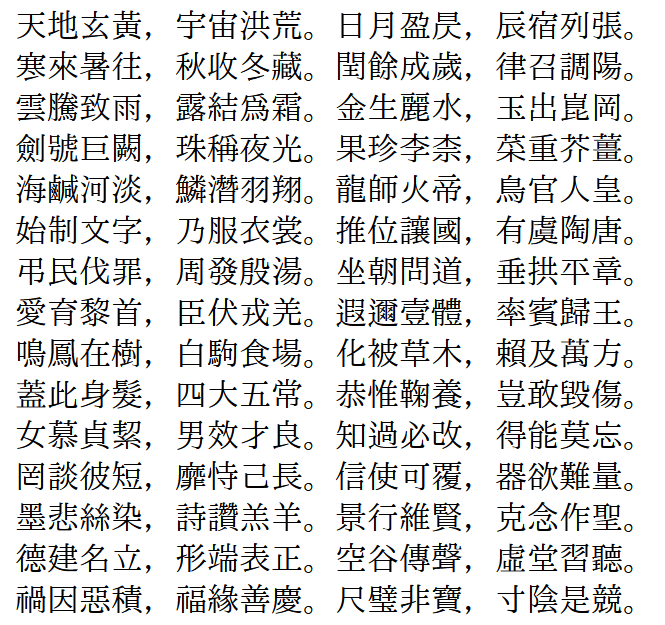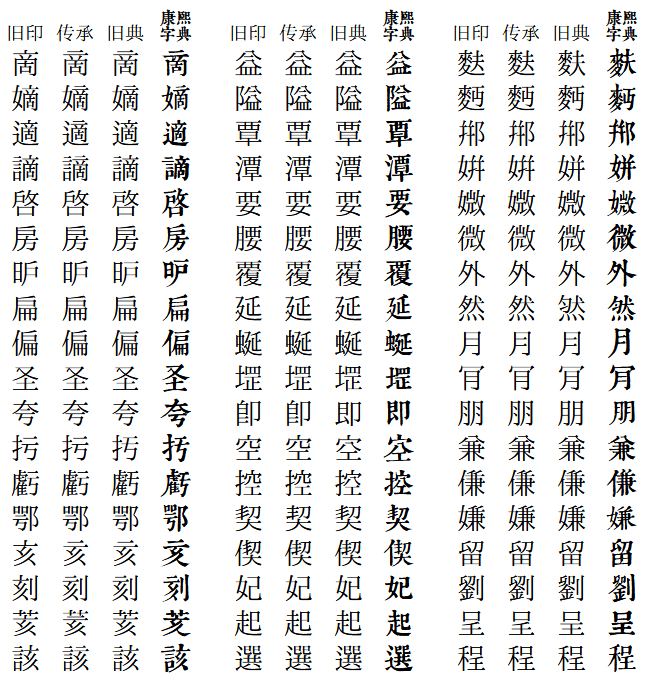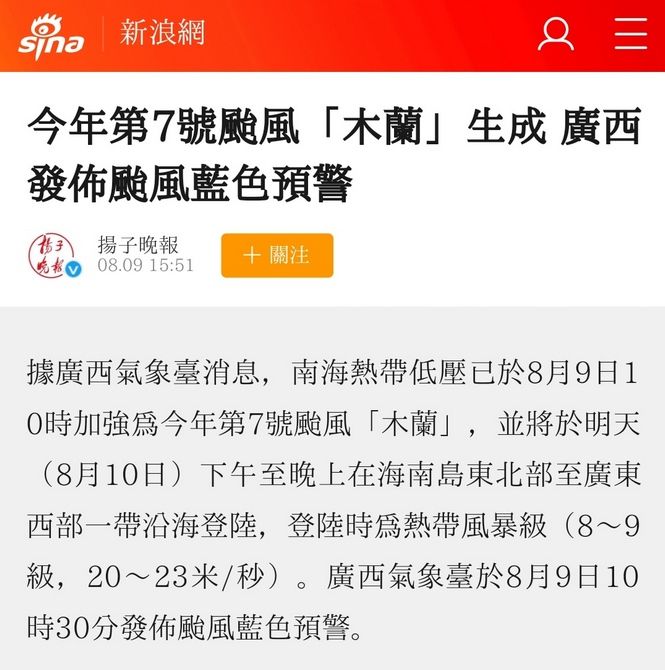
Huaying Mincho 华英明朝 華英明朝
Huaying Mincho 华英明朝是一套拥有传承字形、旧字形风格的中文字体。华英明朝共提供 3 种字形风格,并带有符合 IVD_Charts_Moji_Joho 标准的异体选择器。
1. 华英明朝 旧印体
旧印刷体,字形接近旧版 Windows 新细明体。
2. 华英明朝 传承体
传承字形版,综合参考了包括《康熙字典》在内的经典旧字形资料。
3. 华英明朝 旧典体
接近《康熙字典》中的字形,并保留古籍中汉字部件变化不一的特点。
4. 华英明朝 繁体
传承体基础上制作,简入繁出的字体。通过使用字体的 OpenType 技术,可根据文本的内容动态匹配一简多繁的情況。
简体字的制作
本字体将简化字以“新字”对待,不使用简化字源头上的讹字、俗字、古字等字形。简体字部分在霞鹜新致宋基础上制作,制作中参考了简体对应的繁体字以及中国大陆早期(简繁过度时期)使用过的旧字形简化字。
可通过异体选择符输出 IVD_Charts_Moji_Joho 中的字形。